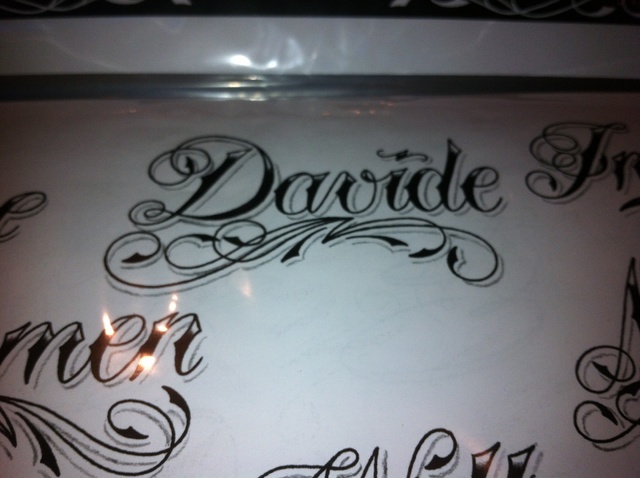
Suche Schrift (Bild - Tattoo)
kennt jemand diese Schrift oder eine so ähnlich aussehende?
Das sind Tattoo-Vorlagen, oder!?
Die sind handgezeichnet. Ähnliches findest du, wenn du bei MyFonts etc. mal nach Tattoo oder Vintage oder so suchst, am besten mit Script. Beim kurzen rüberschauen habe ich das hier entdeckt. Ob der was taugt? Keine Ahnung ...
Ja, sind Tattoovorlagen. Hatte gehofft eine ähnliche, kostenlose Schrift zu finden, um daheim am PC verschiedene Tattoo-Szenarien durchspielen zu können.
Für ein Tattoo würde ich – gerade, wenn es um Typografie geht – lieber ein bisschen Geld springen lassen, um etwas wirklich Einzigartiges zu gestalten, als aus Kostengründen auf einen Gratisfont zurückzugreifen. So ein Tattoo soll ja für den Träger in der Regel etwas ganz Besonderes sein, Individualität betonen, den Träger profilieren. Da mit einer kostenlosen Allerweltsschrift zu agieren würde ich vermeiden. Die Gefahr, dass zig Leute mit der gleichen Schrift herumlaufen, wäre mir zu groß.
Ich würde mir einen Schriftzug, wenn es denn eine Schreibschrift sein soll, von einem Kallligrafen fertigen lassen. Ist vielleicht eine etwas kostspieligere Sache, aber sicherlich wesentlich preiswerter und schmerzfreier als die Laser-OP, mit der man später versucht, sich die Comic Sans wieder von der Pelle zu entfernen. ;-)
Das kann ich nur unterschreiben, wobei Comic Sans ja schon fast wieder was hat, ganz schlimm finde ich diese tausenden von Scriptina-Tattoos die man überall sieht :shock:
Tattoos sind etwas sehr individuelles und sollten für jeden individuell gezeichnet werden. Man kann Fonts als Vorlage nehmen um die gestalterische Richtung zu klären, es sollte aber auf jeden fall noch bearbeitet werden und das muss man können ...
Tatsachenbericht, letzte Woche passiert: Ein junges Mädchen aus meinem Umfeld wollte sich einen Text stechen lassen und wir hatten ausgemacht, dass ich ihr den Entwurf anfertige (und schenke). Letzte Woche kam sie zu Besuch – und hatte das Tattoo bereits fix und fertig auf dem Arm. Als ich vorsichtig nachfragte sagte sie, jaaa, sie habe sich das Ganze ja von mir gestalten lassen wollen, aber der Tätowierer sei immer so ausgebucht und hätte letzte Woche spontan einen Termin frei gehabt – da habe sie zugesagt. Der Text – ein ziemlich langes Filmzitat – wurde ihr für meine Begriffe zu groß auf die Innenseite des Oberarms platziert (bei einem normalen kurzärmeligen T-Shirt schaut es halb aus dem Ärmel hervor) und es wurde ein verschnörkelter Schreibschriftfont verwendet, bei dem leider nicht auf stimmige Buchstabenanschlüsse geachtet wurde. Vermutlich gab es in der verwendeten Schrift keine alternativen, kontextbasierten Glyphen – oder der Tätowierer kannte sich damit nicht aus. Ich fand das echt so richtig schade!
– oder der Tätowierer kannte sich damit nicht aus. Ich fand das echt so richtig schade!
Gibt es eigentlich einen Tätowiererverband, bei dem man Kurse/Seminare dazu anbieten kann :-?
Meist ist es ja gar nicht so schwer/umständlich es besser zu machen, man muss nur wissen, wie :!:
Lohnt es sich überhaupt, typographisch an ein Tattoo ranzugehen? Wenn ich an meinen formvollendeten (die Natur hält den Kreis/die Kugel für ideal) Körper denke, wäre jede Scripttype bis zur Unkenntlichkeit "geboldet" :)
Na ja, die Frage ist ja, wann die figürliche Formvollendung sich manifestiert: vor, während oder nach der Installation der gedruckten Körperkunst. ;-) Sollten die barocken Formen bereits bestehen wenn das Tattoo angebracht wird, dann hat der zu Tätowierende sogar den Vorteil, mehr potenzielle Freifläche für die kunstvollen Nadelarbeiten zu besitzen als der spiddelige Sitznachbar im Tattoostudio. Sollte er der barocken Formen im Anschluss aber jemals wieder verlustig gehen, könnte es zugegebenermaßen zu recht eigenwilligen Transformationen in der Kunstabteilung kommen.
Sehr schön :-) Das wäre dann der erste echte MultipleMaster-Font … das Erscheinungsbild verändert sich mit dem Gewicht :mrgreen: